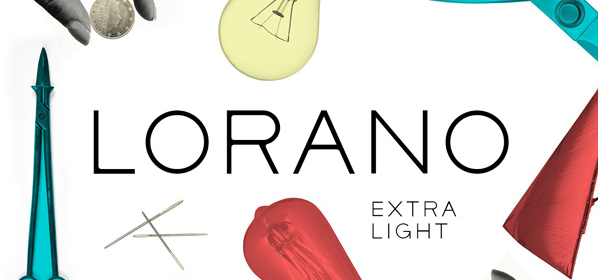
Typographie extralight : Lorano
Lorano est une typographie extralight moderne et inspirée des mouvements minimalistes. Avec ses lignes pures et géométriques, cette typographie est parfaite pour l’impression sur flyers, dépliants, étiquettes, carte des visites ou brochures.